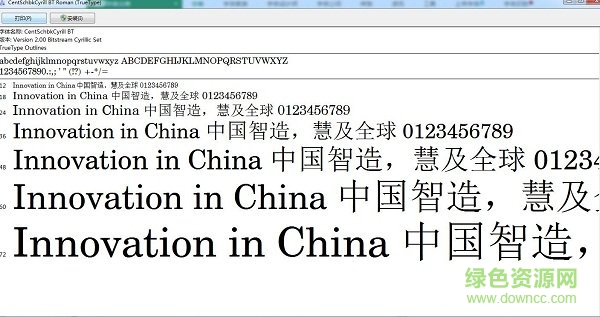
centschbkcyrill bt字體是一款襯線字體,字形秀麗,骨力遒勁,線條粗細(xì)對比明顯,給人的印象是美觀而典雅,可以用在大段落的文章排版中,歡迎大家免費下載!
serif字體容易識別,襯線增加了閱讀時對字母的視覺參照,它強(qiáng)調(diào)了每個字母筆畫的開始和結(jié)束,因此易讀性比較高,